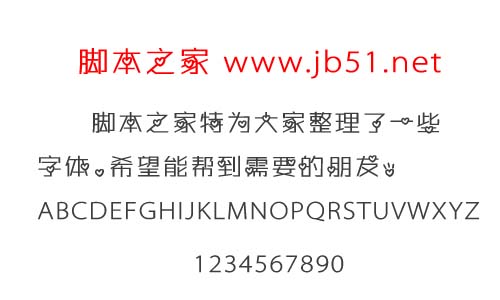
甜蜜小女生手機(jī)字體是一款應(yīng)用于智能手機(jī)方面的中文簡(jiǎn)體漢字,該字體每一個(gè)漢字都帶有心形卡通圖案,效果端正大方,并且字庫(kù)完整,可以應(yīng)用于手機(jī)字體方面,同樣還可以應(yīng)用于廣告設(shè)計(jì)、名片設(shè)計(jì)、包裝印刷、產(chǎn)品設(shè)計(jì)等應(yīng)用,歡迎有需要此款字體的朋友們前來(lái)下載使用。